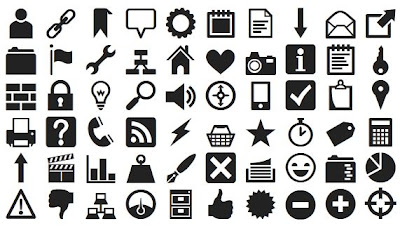
Las tipografÃas de iconos gratis (icon fonts) son una de las formas más eficientes de incluir iconos en una web: cargas un único archivo de fuente y luego usas los iconos como caracteres en cualquier elemento HTML, con color y tamaño controlable por CSS. En este post tienes 10 librerÃas de icon fonts más usadas en 2026, con licencia, número de iconos disponibles, peso del archivo y método de integración (CDN, npm, descarga directa).
Importante: las icon fonts pierden protagonismo frente a los SVG inline en 2026, pero siguen siendo la opción más rápida y ligera cuando necesitas un set completo de iconos sin gestionar archivos individuales. Para 5-10 iconos puntuales, mejor SVG. Para 50+, icon font.
Las más populares y completas
1
Font Awesome
El estándar de facto. Más de 2.000 iconos gratuitos en versión Free, 26.000+ en Pro. Cuatro estilos (solid, regular, light, brands). Integración por CDN, npm o descarga. La opción segura para cualquier proyecto profesional.
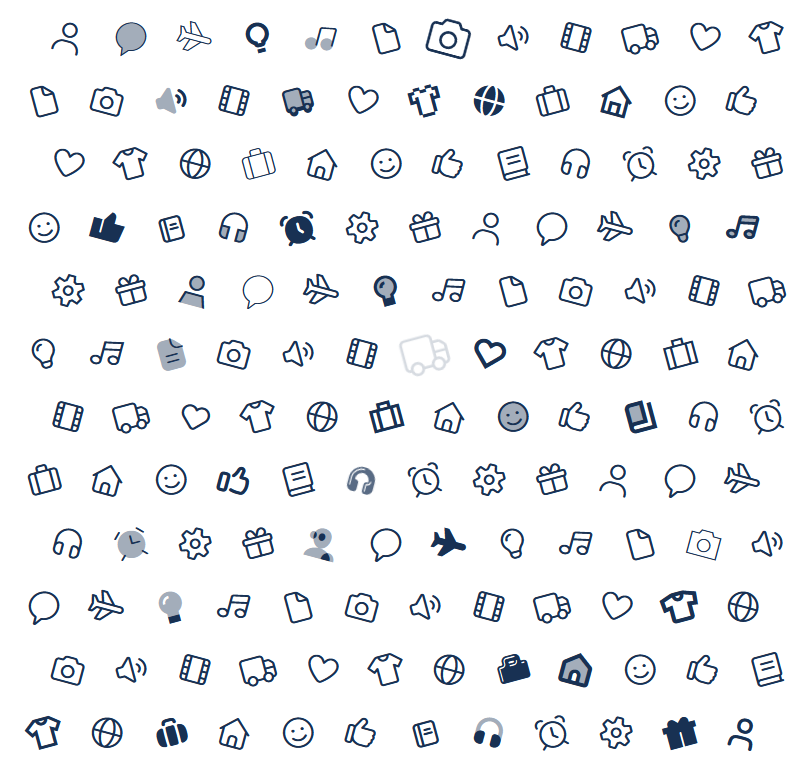
2
Bootstrap Icons
Más de 2.000 iconos open source diseñados por el equipo de Bootstrap. Funcionan independientemente del framework, también como SVG. Licencia MIT total, sin atribución.
3
Iconify
Framework unificado que reúne más de 100 librerÃas de icon fonts (Material, Font Awesome, Lucide, Heroicons, Tabler, etc.) bajo una sola API. Cargas solo los iconos que usas. Mi favorito para proyectos modernos.
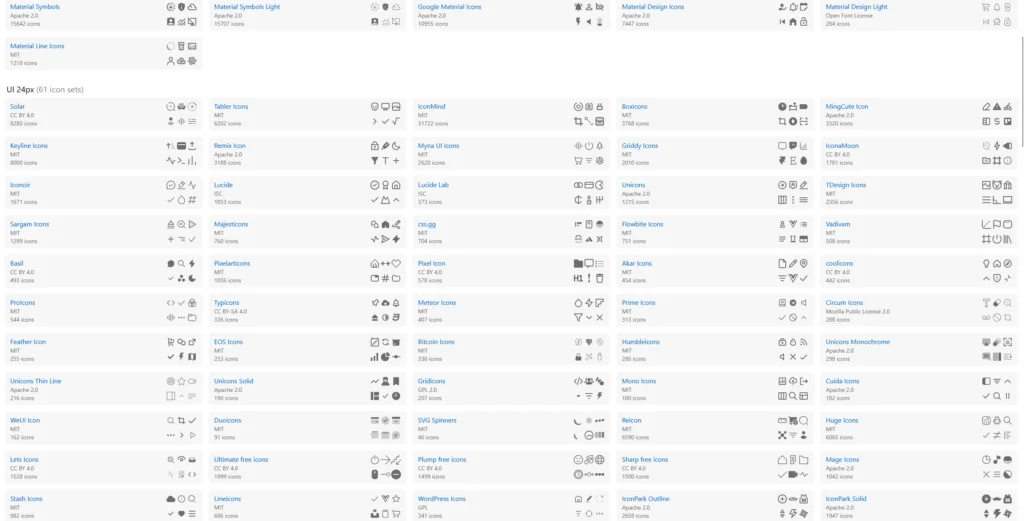
Material Symbols y Google Fonts Icons
4
Material Symbols (Google)
La evolución moderna de Material Icons. Más de 3.500 iconos con cuatro ejes variables (peso, grado, optical size, fill). Es una fuente variable: cargas un único archivo y ajustas el estilo dinámicamente desde CSS. Perfecto si quieres consistencia con apps tipo Google.
5
Lucide Icons
Fork moderno y mantenido de Feather Icons. Más de 1.500 iconos line minimalistas. Limpios, consistentes, ideales para SaaS y apps modernas. Disponibles como fuente, SVG y componentes React/Vue.
6
Heroicons
Iconos diseñados por el equipo de Tailwind. 300+ iconos curados en versión outline (24px) y solid (24px y 20px). Calidad muy alta, perfectos para componer UI moderna con Tailwind.
Icon fonts especializadas
7
Tabler Icons
5.000+ iconos line en formato SVG y fuente. Estilo coherente, lÃneas finas, perfecto para dashboards y herramientas técnicas. Open source MIT.
8
Phosphor Icons
9.000+ iconos en seis estilos (Thin, Light, Regular, Bold, Fill, Duotone). Estilo único, muy detallado, ideal para diseños que se diferencien de la estética genérica de Font Awesome.
9
Remix Icon
2.500+ iconos open source en versión line y solid. Estilo consistente y moderno. Buena alternativa a Font Awesome con menos popularidad y por tanto más distintivo en proyectos profesionales.
10
Ionicons
1.300+ iconos del equipo de Ionic Framework. Diseñados originalmente para apps móviles, asà que vienen con versiones especÃficas para iOS y Material. Ideales si vas a hacer una PWA o app móvil.
Cómo usar una icon font en tu web
Tres formas según tu caso:
Para optimizar performance: 1) Carga solo los iconos que usas (con npm o subset). 2) Usa font-display: swap para que no bloquee el renderizado. 3) Para 5-10 iconos puntuales, SVG inline es mejor que icon font completa.
Icon font vs SVG: ¿cuándo usar cada uno?
| Criterio | Icon font | SVG |
|---|---|---|
| Cantidad de iconos | Mejor con 50+ | Mejor con 1-20 |
| Peso de carga | Fijo (el archivo entero) | Solo lo que usas |
| Color | Un solo color por icono | Multicolor posible |
| Animación | Limitada (CSS) | Total control con CSS/JS |
| Accesibilidad | Requiere aria-label | Mejor (con title/desc) |
¿Por qué algunos iconos se ven borrosos?
Las icon fonts renderizan como texto. A tamaños que no coinciden con el tamaño original del icono (tÃpicamente 16, 24, 32, 48px) pueden verse borrosos. Usa tamaños múltiplos de la rejilla original (Material Symbols usa 24px, Heroicons 20/24px). Para mejor nitidez en cualquier tamaño, usa SVG inline.
Conclusión
Tres caminos. Para proyectos estándar con muchos iconos: Font Awesome o Bootstrap Icons. Para proyectos modernos con design system: Lucide, Heroicons (Tailwind) o Phosphor. Para framework unificado: Iconify. Disfrútalas!